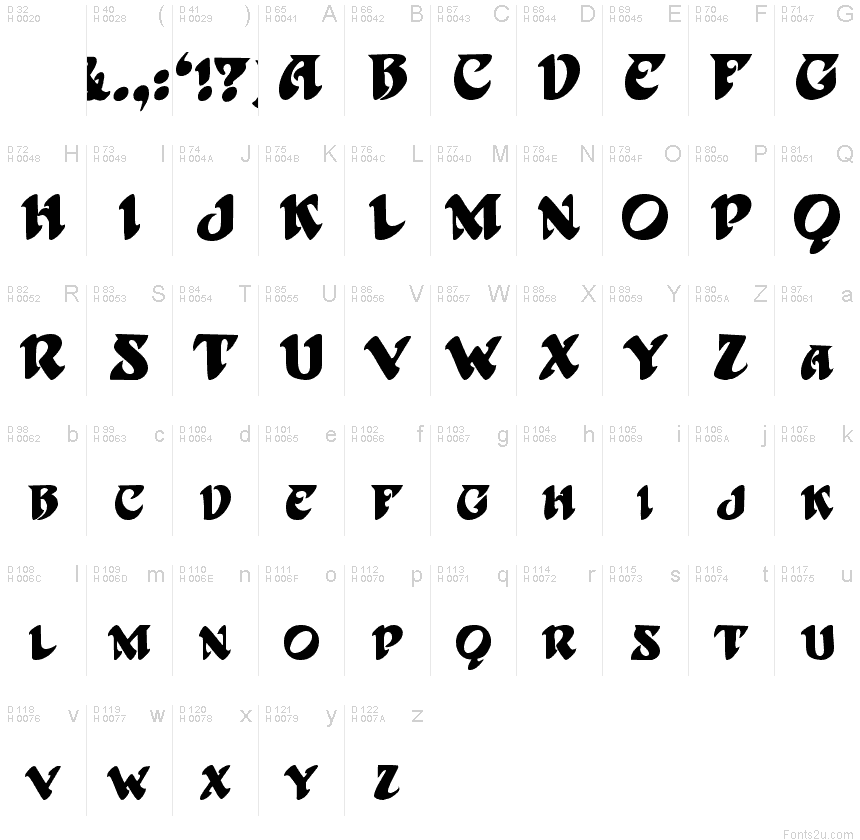
Harbinger di David F. Nalle è un font display retro gratuito che sembra estratto da una vecchia mappa fantasy o dalla copertina di un album metal. Le forme pesanti, quasi inchiostrate, e le curve affilate e affusolate conferiscono a ogni lettera un aspetto drammatico, quasi scolpito, mentre il ritmo serrato rende le parole simili a sigilli arcaici. Si percepisce un'energia rituale e medievale che crea immediatamente un'atmosfera cupa e misteriosa.
Harbinger è un font gratuito che dà il meglio di sé su copertine di libri fantasy, loghi per band metal o gothic, titoli di videogiochi, poster horror, fanzine a tema occulto e nel branding di rievocazioni storiche. Le sue sagome robuste e scolpite si prestano magnificamente alle grandi dimensioni, dove ogni curva e punta può risaltare. Abbina Harbinger a un font sans serif geometrico pulito nel testo più piccolo per mantenere la leggibilità, lasciando che il titolo faccia il lavoro narrativo.